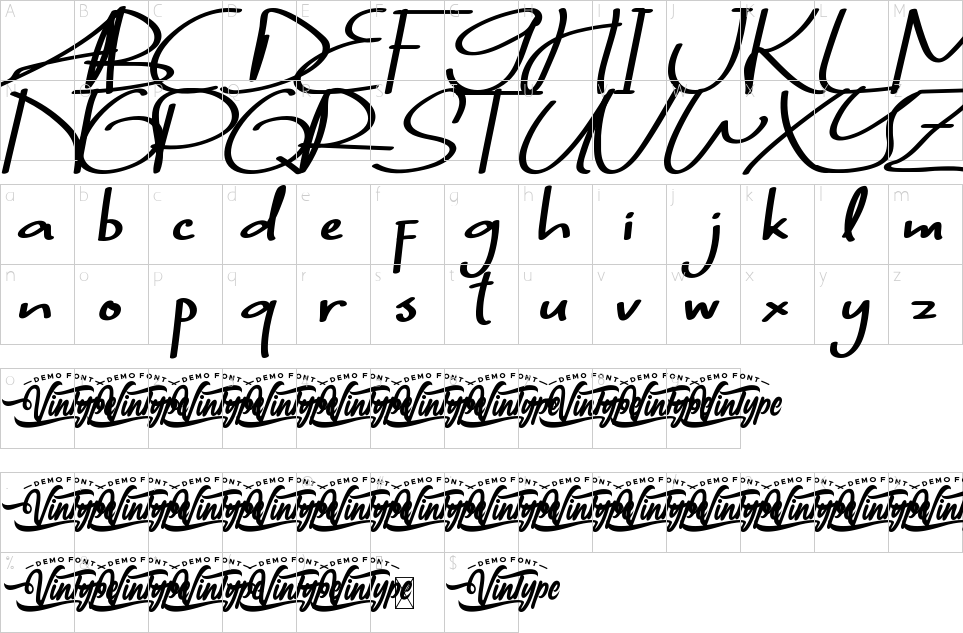
Dannia Roseline Font – Download Grátis
A Dannia Roseline é uma fonte moderna e elegante criada pelo VinType que agora está disponível gratuitamente para download tanto no Windows quanto no Mac. Esta fonte foi projetada para complementar designs de texto, oferecendo linhas leves e textura suave que podem se destacar em qualquer layout editorial ou design gráfico. Com seu estilo delicado e versátil, a Dannia Roseline é uma escolha excelente para designers, profissionais da mídia social, ou até mesmo aqueles que desejam adicionar um toque de sofisticação aos seus projetos digitais. Além disso, ela pode ser uma ótima opção para criações em redes sociais e designs pessoais. Com 695 downloads, a Dannia Roseline já provou sua qualidade e popularidade entre designers de todo o mundo. Se você está procurando por uma fonte moderna e agradável que vai desde o título até as letras finas de seu design, não há como resistir à delicadeza da Dannia Roseline.